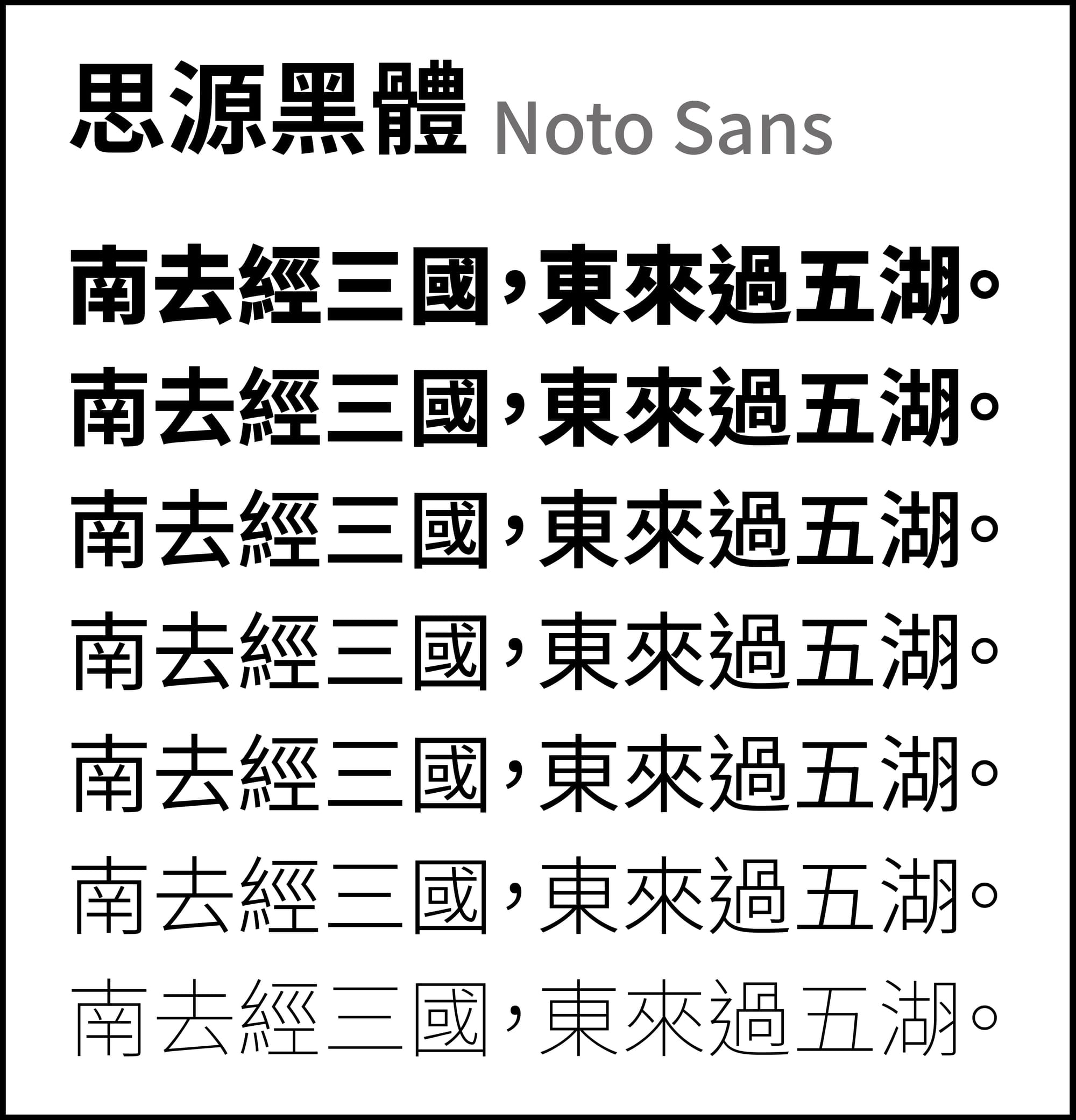
免費下載的黑體有哪些?免費?開源?使用差異大解析!
在下載字體之前我們應該先來好好了解一下背後的概念,字體是透過設計師們的花時間努力產出的結晶,不同的字體之間當然也有授權類型的差異,當你找到喜歡的字體下載後,是否有確認這些心血有被正確使用呢?
開源?免費?可商用?
開源黑體大當家
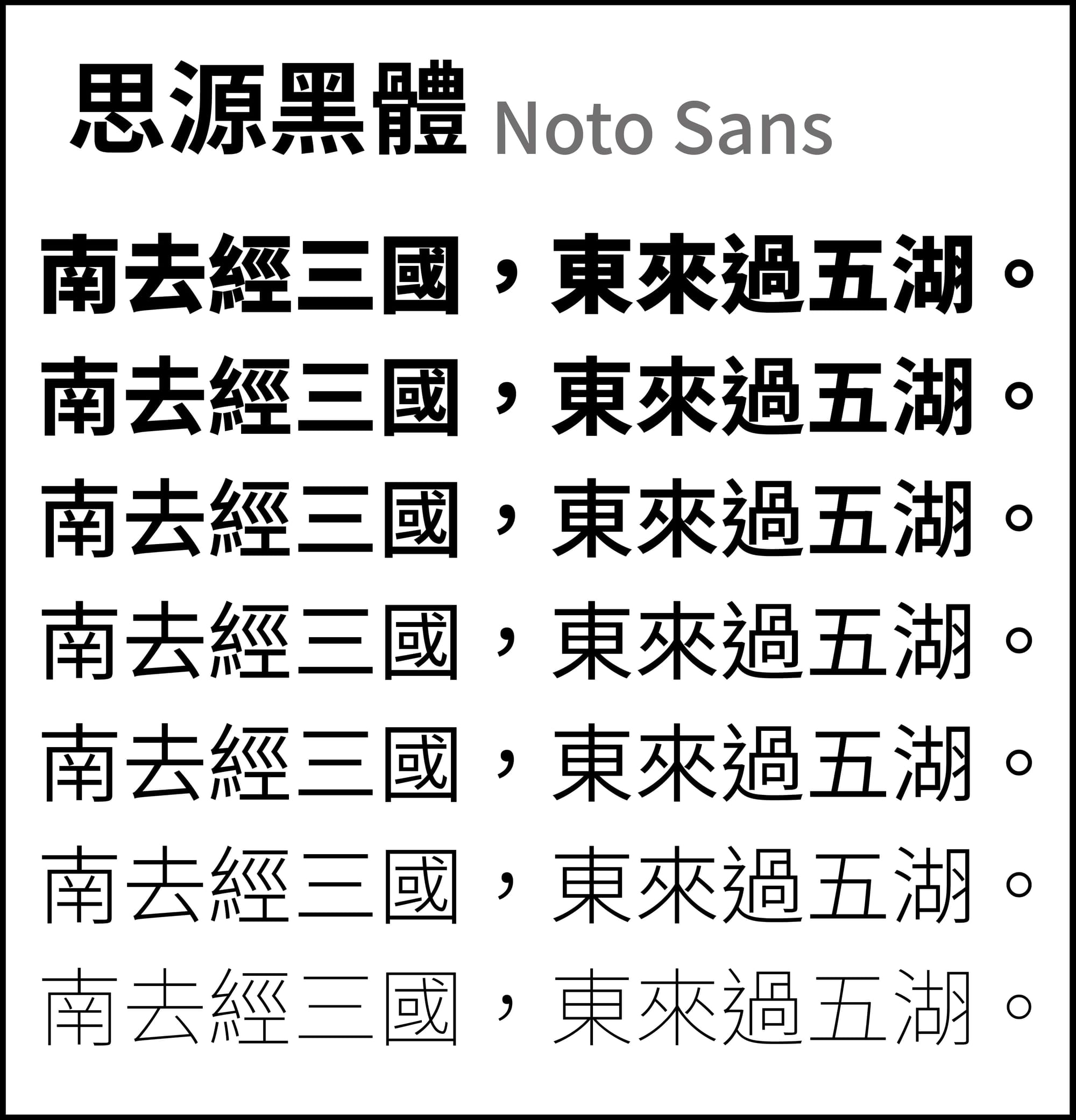
思源黑體使用了 SIL OFL 授權開源,思源黑體涵蓋了中日韓等多個語系,追求著跨語系之間的一致性與美感,簡約耐看的無襯線設計,還擁有七種粗細可調節,思源黑體以他完整的框架衍生出了非常多種的字體,是開源黑體的大當家。
思源黑體家族
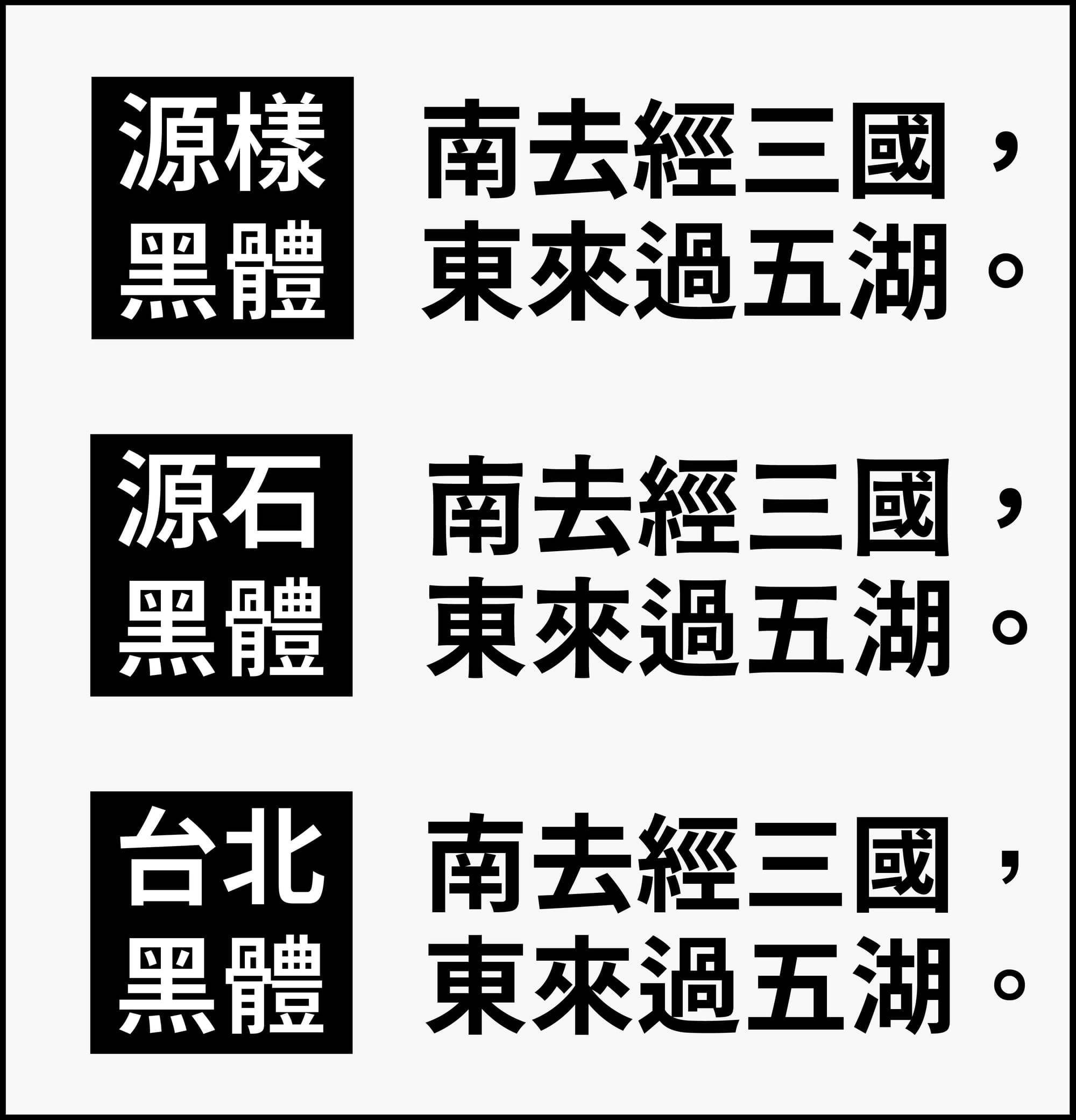
思源黑體衍生出了源樣黑體和源石黑體以及台北黑體,源樣黑體更改了原本的寫法使用了傳承字的寫法,多了一種典雅的感覺,在糸部和辶部的地方可以發現和思源黑體的差異。
源石黑體則在筆畫上調整了曲度,顯得在單一筆畫在粗細度上多了一點動態感,在整體上更加具有溫度。
台北黑體是針對繁體中文做調整,粗細度只有三種模式可以調整,在傳承字的寫法上又穿插著新型字的寫法,新舊融合的風格在使用上多了一點的靈活和隨興。
更多黑體!
IBM Plen Sans
IBM Plex Sans 也支援眾多語系,且有八種粗細度調整,視覺上在撇捺的部分可以明顯感受到粗細變化,流線型的筆畫給人時尚的感受。
LINE Seed
LINE Seed 從名稱上可以很容易發現這款字體就是由 LINE 釋出的,字體原本只有日韓泰語版本,但在之後也更新了繁體中文版。
饅頭黑體
由饅頭基於日文字體 デラゴシック, 修改而成針對繁體中文的字體,寬扁的造型重量感十足,用在標題或海報都方常適合。